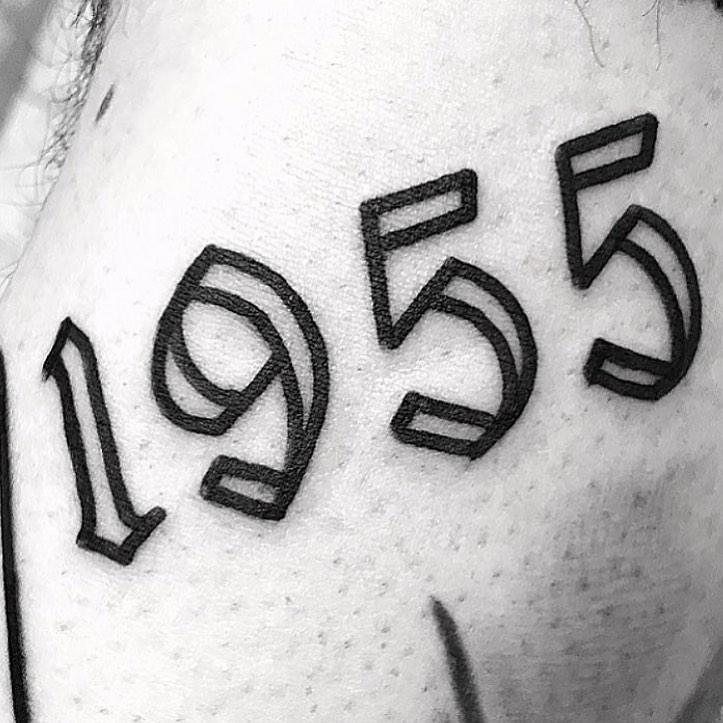
Hallo, ich suche diese Schrift. Hat jemand eine Idee? Ich habe leider keine Quelle. Ich habe jede Menge Gothic/Fraktur/Tattoo-Fonts durchgesehen, aber die meisten sind zu schnörkelig. Diese hier ist so schön einfach. Bin für jeden Hinweis dankbar!